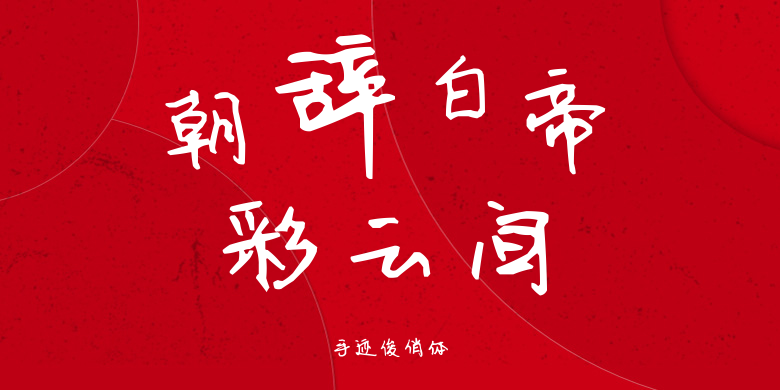
手迹俊俏体
手迹俊俏体,这款字体结构工整、笔画清晰,兼顾美观与易读性,适用于标题、正文、海报、包装、LOGO 等多种场景。字形优雅稳定,风格百搭耐看,适配日常排版与创意设计,让文字呈现更舒适、更具质感。手迹俊俏体一笔一画,皆是细节,以均衡的比例、流畅的线条打造舒适视觉体验,字形端正大气,风格简约现代。无论是商业设计、品牌宣传还是日常排版,都能轻松驾驭,让文字更有格调与力量。手迹俊俏体字体下载。